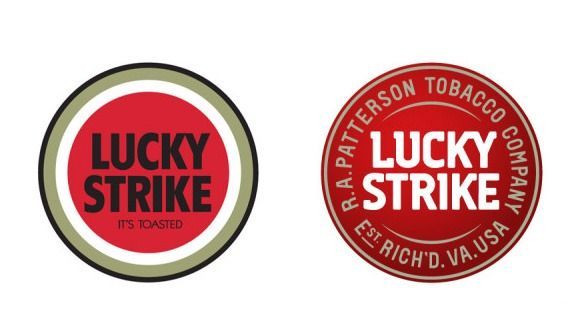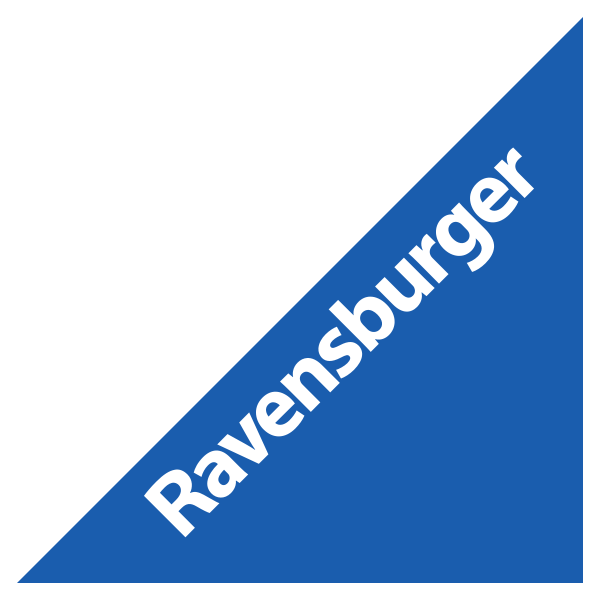
Jägermeister-Schrift gesucht
ich wollte fragen ob mir jemand sagen kann aus welcher Schrift der Jägermeister
Schriftzug ist, und wer sie vielleicht geschnitten hat. Das beste was ich bis jetzt gefunden
habe war die OLD LONDON.
Ein Bild sagt mehr als …
Es wäre noch interessant zu wissen, warum du das wissen willst?
Bei Logos dieses Alters ist in 95% der Fälle ohnehin keine Satzschrift vorhanden, sondern das Logo wurde eben für diese Anwendung entworfen. Dass man Logos aus Schriften »setzt«, gibt es erst seit gut 25 Jahren.
Ich studiere Digital Publishing und in da habe ich das Fach Typographie.
Unsere Klausur besteht darin von einem bestimmtem Buchstaben (meiner ist des R) einige Bilder
zu machen und von diesen Schriften dann die Schriftart heraus zufinden. Dannach müssen wir über ein Bild einen Vortrag halten.
Außererdem habe ich mal Ritter Sport( wobei mich hier das "Ritter" interessiert), Ravensburger und Lucky Strike ins auge gefasst.
Ich habe auch schon der Firma Jägermeister ein e-mail geschrieben und als Antwort bekommen, dass es sich um die Schwabacher Schrift handelt...
,aber irgendwie sieht das nicht gleich aus.
Vielleicht könnt ihr mir ja bei den anderen auch helfen?
Eine Schwacher ist das ganz sicher nicht, niemals ...
Das ist eher was ›Gotisches‹, eine Art Textura, die aber, wie Ralf schon sagte, extra gezeichnet ist ...
Ansonsten denke ich, dass wenn du hier konkrete Fragen stellst, man dir auch gerne hilft. Aber etwas eigene Recherche-Arbeit sollte dabei auch erkennbar sein.
Ich würde in diesem Zusammenhang auch keinen älteres Logo nehmen, denn damals wäre es für die Grafiker extrem schwierig, sich erst einmal einen Drücker zu suchen, der die gewünschte Schriftart überhaupt besaß, um dann sich den Text setzen zu lassen. Letraset oder gar Computerfonts gab es ja noch nicht, zudem wollten die Auftraggeber ohnehin eine ganz eigene Schrift. So wurde dann so ein Logo von einem Grafiker, der in Kalligraphie begabt war, komplett frei gezeichnet. Zudem wurde die so einmal gestalteten Logos oft noch weiter verfeinert.
Wenn du dir also die Vorlage auswählen kannst, nehme etwas, das tatsächlich in Blei gesetzt wurde, wie z.B. alte Anzeigen in Zeitungen, und da eben nicht das Logo.
Schau dir nur einmal hier dieses Schildermaler-Video an. Der ist ja noch ein Vertreter der alten Zunft. So oder so ähnlich wurden früher fast alle Text-Logos produziert.